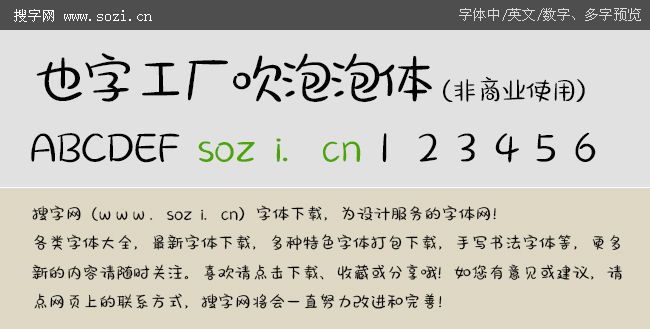
也字工廠吹泡泡體
搜字網(wǎng)給大家提供一款也字工廠吹泡泡體(非商業(yè)使用)中文字體下載,也字工廠吹泡泡體是一款手寫風(fēng)格的卡通字體,字體書寫流暢自然,字形充滿趣味。具有很好的視覺效果。適合應(yīng)用于藝術(shù)設(shè)計、平面宣傳設(shè)計、網(wǎng)頁設(shè)計、海報設(shè)計等應(yīng)用(此字體為個人非商用版,商用可以聯(lián)系:官方網(wǎng)址:https://yefont.com/home,聯(lián)系方式:13798980448)。